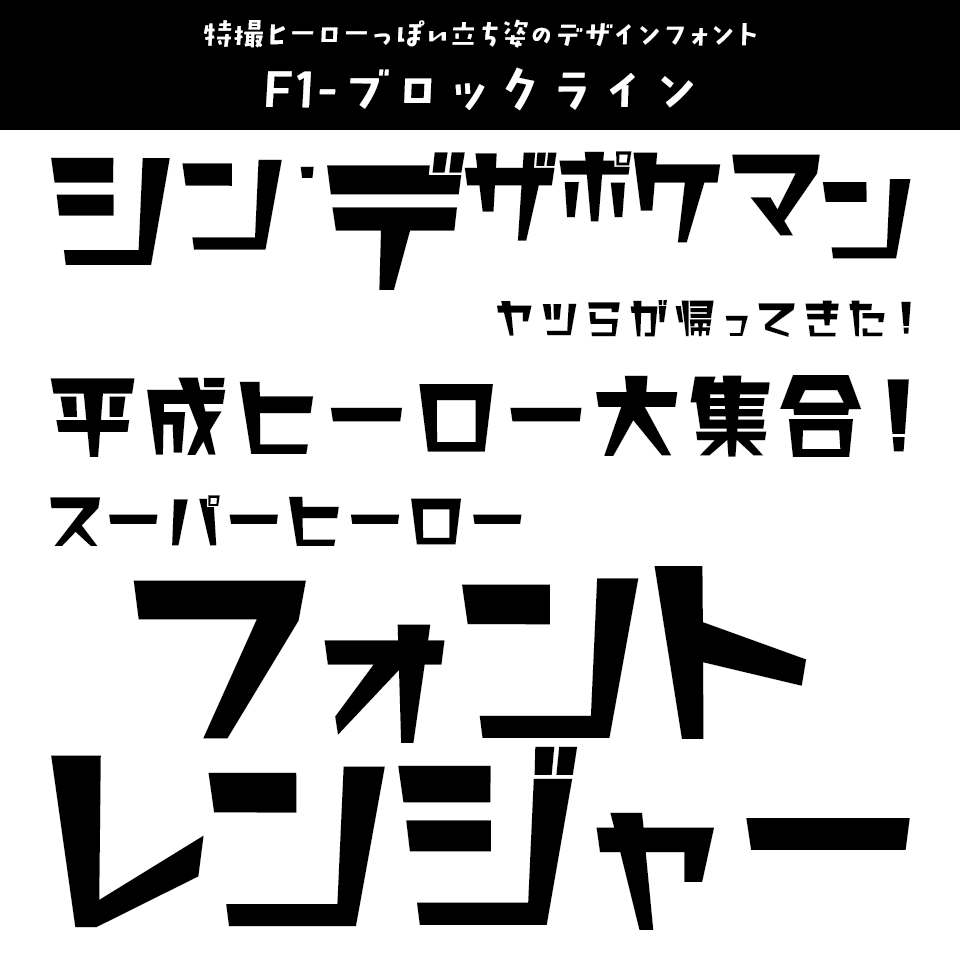
「特撮」に合うフォント:特化型 目的別フォントガイド #130
「特撮」に合うフォントをスタッフが選びました
「特撮」に合うフォント F1-ブロックライン
特撮ヒーローっぽい立ち姿のデザインフォント
F1-ブロックライン【FONT1000】
「特撮」に合うフォント F1-ブロックライン
外側の線を斜めにした立体的なフォルムのデザイン。堂々とした振る舞い、立ち姿が特撮ヒーローっぽさを感じさせるデザインフォントです。
「特撮」に合うフォント JTCウインZ10
直線ならではの力強さや迫力を持つ特撮風デザインゴシック
JTCウインZ10【ニィスフォント】
「特撮」に合うフォント JTCウインZ10
直線だけで構成された極めて珍しいデザインの書体。直線ならではの力強さや迫力がありながら、バランスの崩れがないのも大きな特長です。
「特撮」に合うフォント DF綜藝体 W9
太く正方な字形が特撮モノのタイトルっぽいデザインフォント
DF綜藝体 W9【ダイナフォント】
「特撮」に合うフォント DF綜藝体 W9
通常のゴシック体よりも太く正方な字形を採用し、1文字の中に生じる余白部分を均等化、また、まっすぐ伸びた線の曲がりやハネの先端部分をややカーブさせる事で独特のポップさが生まれたデザイン書体です。
「特撮」に合うフォント モトヤ ゴチカ8
特撮モノのような躍動感とチカラ強さを持つデザインフォント
モトヤ ゴチカ8【モトヤ】
「特撮」に合うフォント モトヤ ゴチカ8
ゴシック体をベースとして横線やハライに筆文字の勢いを表現することで、躍動感とチカラ強さを感じさせる書体です。
「特撮」に合うフォント TA DON
太くドーンとした存在感が特撮モノにぴったりのデザインフォント
TA DON【FONT1000】
「特撮」に合うフォント TA DON
太く安定感のある書体です。縦・横のラインを中心に構成して安定感を強調したデザイン書体。
「特撮」に合うフォント 親剛体
どっしり力強い極太フォントがロゴにぴったり
親剛体【楽フォント】
「特撮」に合うフォント 親剛体
縦画と横画の線幅のコントラストによって生み出される圧倒的インパクトと、滑らかでやわらかいカーブの組み合わせが特徴的な書体です。密度の高い大胆なデザインながら、カッティングに几帳面な正方形を意識することにより、重量感に負けない可読性を保っています。線幅のスタイルは文字ごとに自由に設計されており、どっしりとした文字組みの中にも、どこかリズミカルな印象を。その名の通り、「親しみやすく」「つよい」。オープンでインパクトあるイメージを求めるロゴや見出しに最適です。
「特撮」に合うフォント やわらかドラゴン
とがったフォルムが往年の特撮っぽい
やわらかドラゴン【ヤマナカデザインワークス】
「特撮」に合うフォント やわらかドラゴン
力強くもあり、どこか柔らかい。そんなイメージの日本語フォントです。インパクトを持たせたい時、優しい印象を持たせたい時に。
「特撮」に合うフォント DFひびゴシック体 W14
特撮の激しいバトルにぴったりの力強いフォント
DFひびゴシック体 W14【ダイナフォント】
「特撮」に合うフォント DFひびゴシック体 W14
超極太ゴシック体をベースに、筆画の一部に切り込みを入れることでまばらな印象にデザインされています。特撮の激しいバトルにぴったりの力強いフォントです。
「特撮」に合うフォント TA 石ちゃん
荒々しいフォルムが特撮モノのタイトルっぽいデザインフォント
TA 石ちゃん【FONT1000】
「特撮」に合うフォント TA 石ちゃん
大きな石を削って文字を作ったイメージで制作された、荒々しいフォルムのデザイン書体。
「特撮」に合うフォント HG創英イオリ書体
昭和の特撮のサブタイトルっぽいデザインフォント
HG創英イオリ書体【リコー】
「特撮」に合うフォント HG創英イオリ書体
昭和の特撮モノのサブタイトルに使われていそうな力強くどこか不気味で不思議な魅力のある極太フォント。
「特撮」に合うフォント DF平成明朝体 W9
なんでもない写真が特撮っぽくなる明朝体
DF平成明朝体 W9【ダイナフォント】
「特撮」に合うフォント DF平成明朝体 W9
平成明朝体は、直線を多用し必要のない曲線を省略する事で、ストロークがシンプルになり、文字に力強さや迫力を感じさせる書体になっています。少し長体をかけて文字を詰め気味でキャプションを打ち込むだけで、何でもない風景写真が特撮映画のワンシーンに見える不思議な明朝体です。